50+ потрясающих ретро-шрифтов от 50-х до 90-х годов
Опубликовано: 2022-02-22Ретро веб-шрифты наполнены характером, и они могут придать вашему веб-сайту или проекту графического дизайна ностальгическое ощущение. Но найти шрифты для определенного десятилетия непросто, поэтому мы составили этот список винтажных шрифтов, организованных по десятилетиям.
От яркой и бодрой типографики 90-х до элегантного шрифта, созданного по образцу профессионального леттеринга 50-х, «ретро» — это разнообразный дескриптор, и здесь есть из чего выбрать.
Что такое ретро-шрифты?
Даже те, кто никогда не был свидетелем этого, знакомы с популярной типографикой 20-го века. От ранних комиксов 50-х до смелых и ярких сценариев 60-х и 70-х и забавных мультяшных шрифтов 90-х, каждая эпоха была наполнена уникальной индивидуальностью.
«Ретро» описывает шрифты, которые либо были созданы в 20-м веке и дожили до повседневного использования, либо были созданы современными дизайнерами, пытающимися подражать одному из этих стилей.
Вывески, плакаты, обложки, реклама, телешоу и видеоигры, логотипы и известные бренды 1950–1990-х годов служат источником вдохновения.
Эти смелые ретро-шрифты лучше всего смотрятся в больших размерах, независимо от того, используете ли вы их в полиграфическом дизайне, электронных письмах или демонстрируете на своем веб-сайте.
Винтажные ретро-шрифты 50-х годов
1. Профсоюз
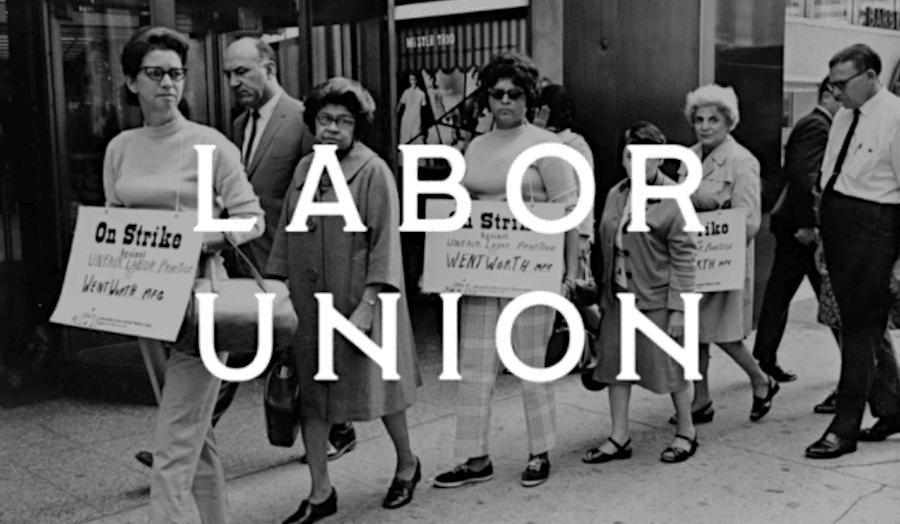
Шрифт Labor Union, вдохновленный типографикой середины 20-го века, хорошо впишется в любой проект, требующий винтажного индустриального стиля. Это полностью бесплатно, в том числе для коммерческого использования, так что смело добавляйте эти жирные засечки в любой проект.
2. ТУОМ
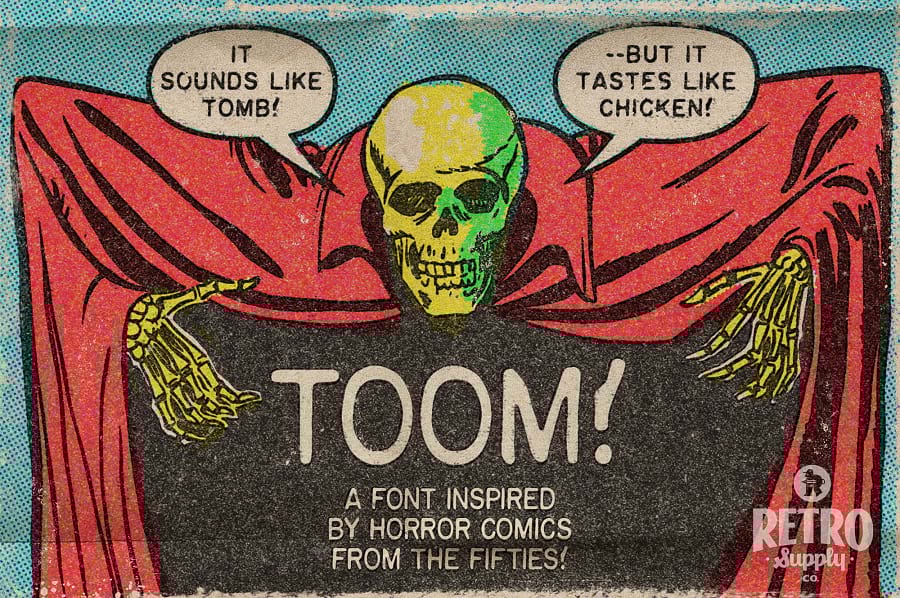
TOOM в значительной степени основан на работе EC Comics, компании, которая печатала комиксы ужасов, темного фэнтези и научной фантастики в 1940-х и 1950-х годах. Их фирменный сверхъестественный текст был создан с помощью машины, имитирующей рукописный стиль. Любителям старых комиксов понравится.
3. Дни собак
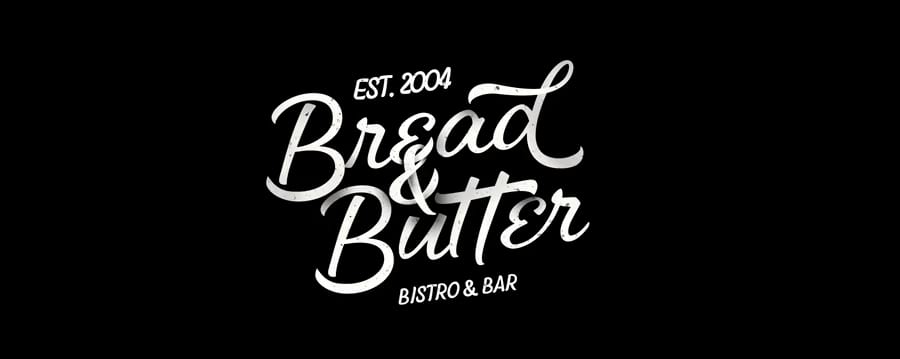
Dog Days удается идеально передать популярный в прошлом рукописный сценарий кисти для каллиграфии. Он заимствует свой стиль из рекламы винтажных купальников. Но хотя он может быть основан на старомодном шрифте, он обладает множеством поразительных функций OpenType.
4. Фонтанчик с газировкой
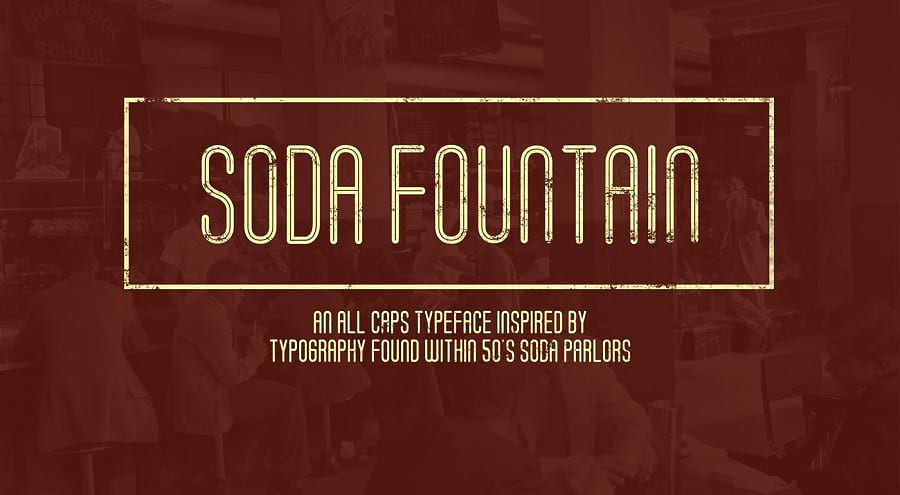
Soda Fountain — это шрифт с заглавными буквами, основанный на типографике закусочных и баров с газировкой 1950-х годов. Его плавные, мягкие линии выглядят совершенно винтажно, и он бесплатен для личного и коммерческого использования.
5. Путешествие
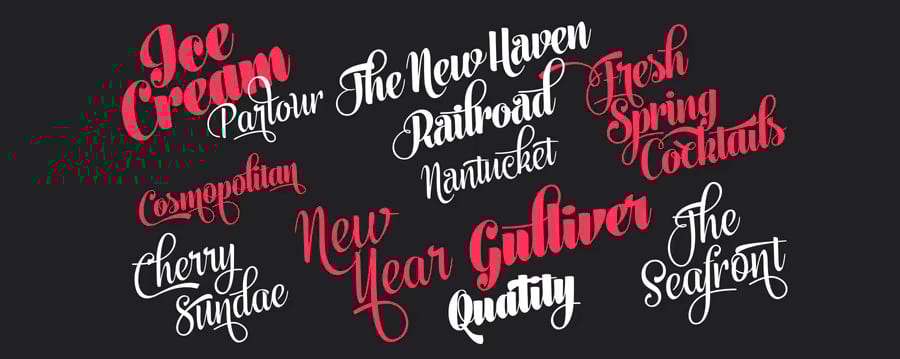
Journey — это винтажный шрифт с кистью, дополненный орнаментами и альтернативными символами, которые делают его очень универсальным. Если вы пытаетесь подражать элегантной рекламе 50-х годов, попробуйте это.
6. Свежая пресса
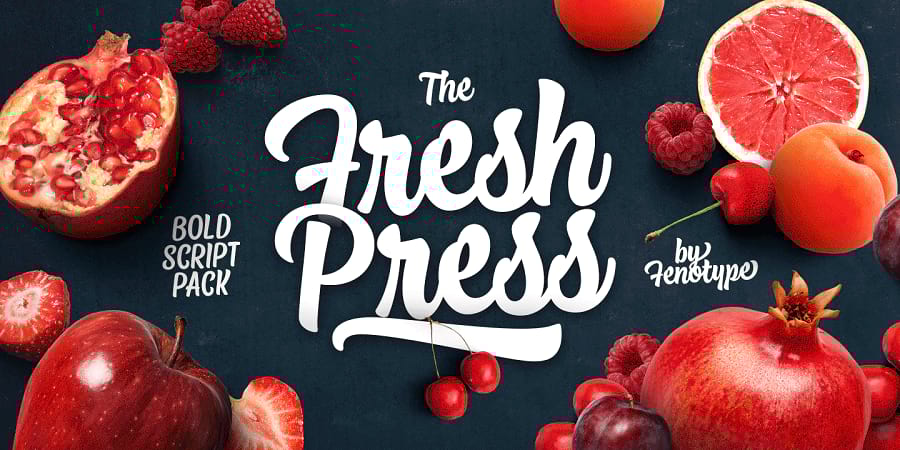
Многие курсивные шрифты 50-х тонкие и элегантные, но Fresh Press предлагает гораздо более смелый вид, который наверняка удивит. Есть также более грубая, более текстурированная версия шрифта, если вы хотите почувствовать старомодность.
7. Порошковый сценарий
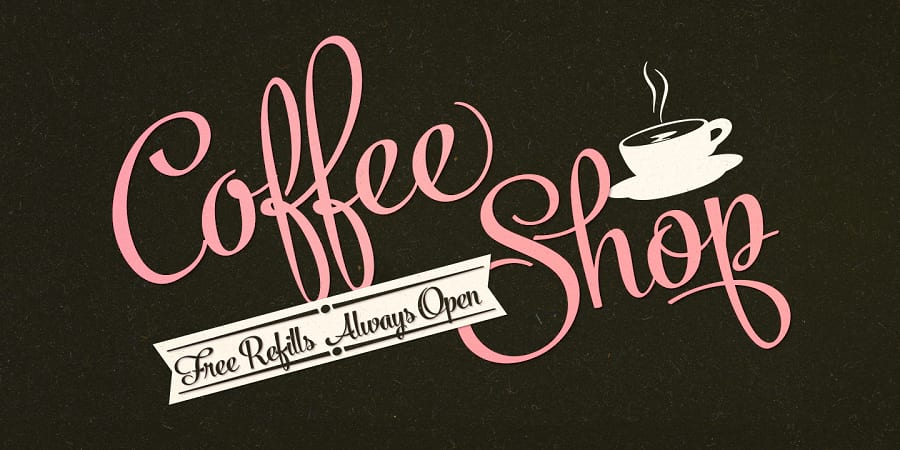
Нужно что-то гламурное? Попробуйте порошковый скрипт. Изящные завитушки на каждой букве, а шрифт включает 800 глифов на вес, поэтому каждая буква, которую вы набираете, уникальна.
8. Кувшин
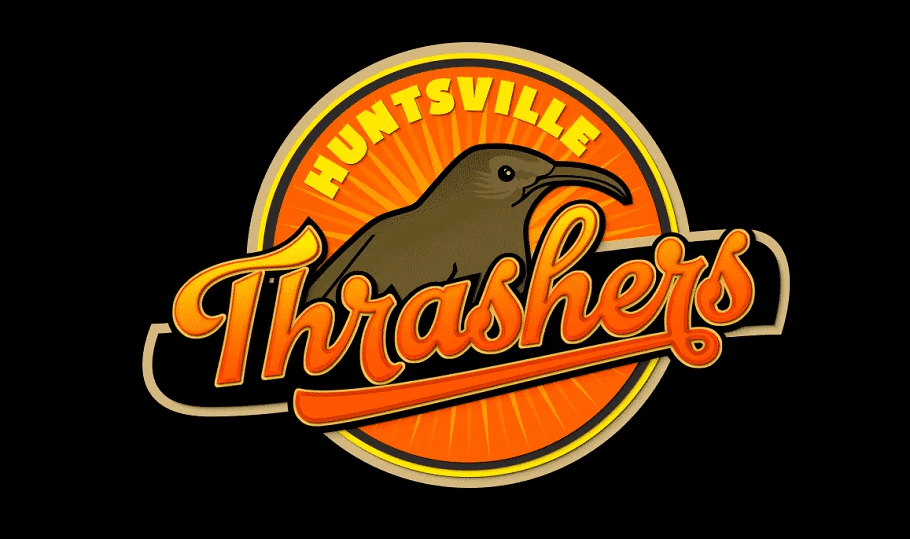
Питчер пытается передать немного вкуса американской культуры 1940-х и 1950-х годов с помощью смелого шрифта, полного индивидуальности. Доступна как чистая версия, так и текстурированная, более гранжевая альтернатива.
9. Трафарет 1952 г.
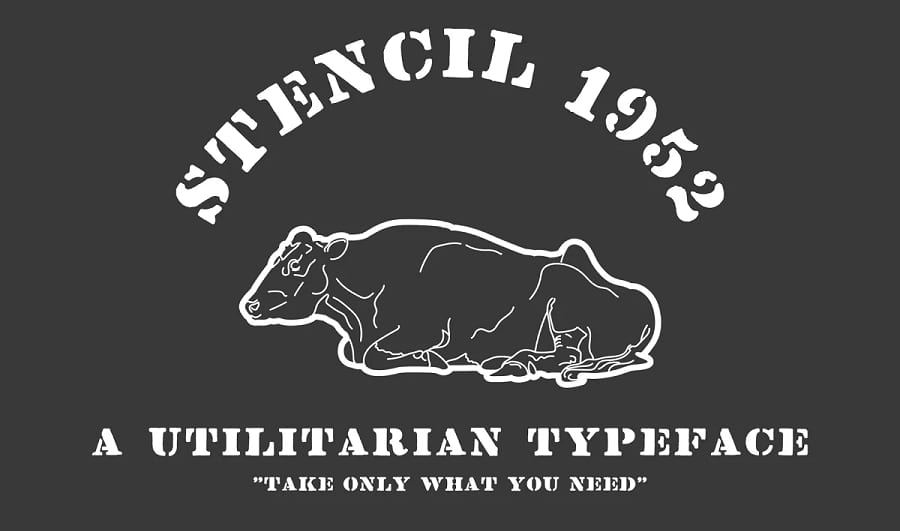
Stencil 1952 — это чистый и серьезный трафаретный шрифт, обнаруженный в старой книге по типографике, так что вы знаете, что это реальная сделка. Многие шрифты пытаются подражать типографике той эпохи, но этот взят прямо из прошлого.
10. Коттедж Санс
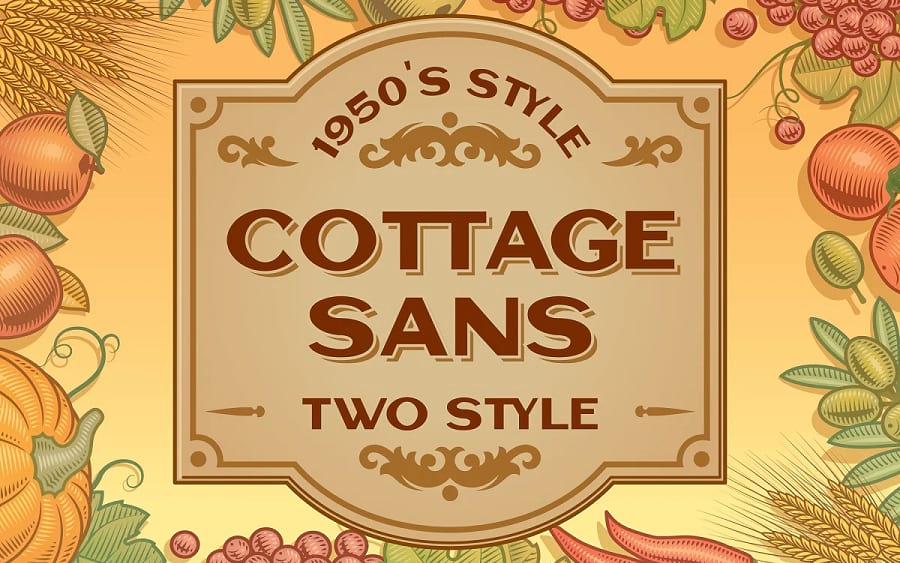
Cottage Sans — красивый деревенский шрифт с правильным и закругленным стилем. Строгие шрифты без засечек будут хорошо смотреться в любом дизайне, чтобы передать старую ностальгическую атмосферу.
Отличные шрифты 60-х
11. Рэмдон
В шрифте Ramdone вы можете увидеть переход от кистей 50-х годов к чему-то похожему, но с немного большей бодростью. Он также включает в себя эффект выдавливания, так что вы можете сделать свой шрифт трехмерным.
12. Заводной
Эти смелые 3D-сценарии были популярны в 60-х и 70-х годах, и Groovy отлично справляется с этим. Поскольку эффект выдавливания поставляется вместе со шрифтом, этот шрифт легко сделать похожим на изображения для предварительного просмотра.
13. Далеко!
Вдохновение Far Out немного слабее, но вы все равно можете увидеть вплетенный в него уникальный стиль 60-х. Поскольку он бесплатен для всех типов использования, вам следует попробовать его, если вы хотите что-то немного другое, но все же явно принадлежащее этой эпохе.
14. Молочник
Это интересно; Milkman сочетает ретро и современную типографику, чтобы создать что-то, что легко вписывается в 21 век, но сохраняет винтажную атмосферу.
Резюме
Дико разнообразная культура отличала 20-й век от десятилетия к десятилетию. Каждая из этих эпох может предложить что-то уникальное. Ищете ли вы элегантный шрифт кисти или бодрый дисплейный шрифт, один из этих 50+ ностальгических шрифтов найдет то, что вам нужно.